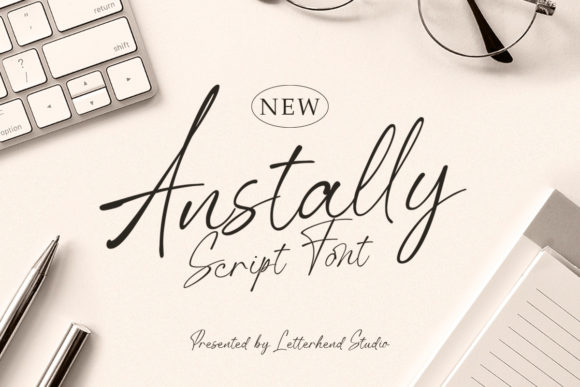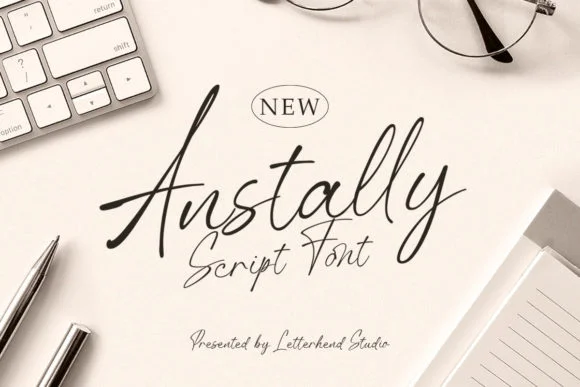
Название: Anstally Script Font (2021)
Anstally Script - это прекрасный и неподвластный времени рукописный шрифт.
Это лучший выбор для создания привлекающих внимание логотипов, брендинга и цитат.
Каждая буква имеет уникальный и красивый оттенок, благодаря которому ваш дизайн оживет!
Название: Anstally Script Font (2021)
Anstally Script - это прекрасный и неподвластный времени рукописный шрифт.
Это лучший выбор для создания привлекающих внимание логотипов, брендинга и цитат.
Каждая буква имеет уникальный и красивый оттенок, благодаря которому ваш дизайн оживет!